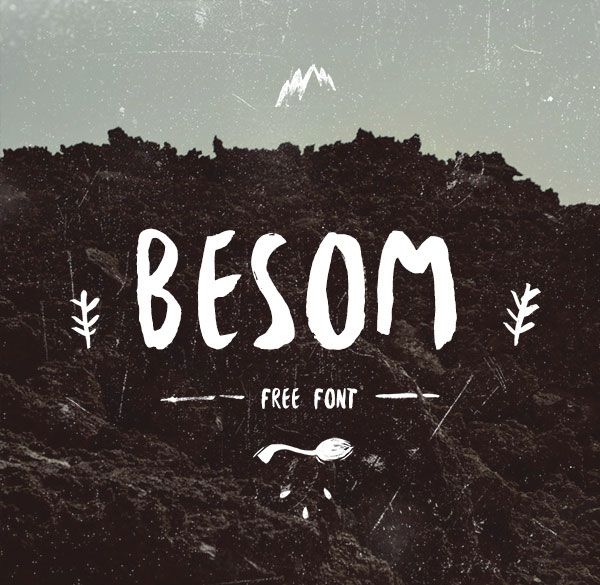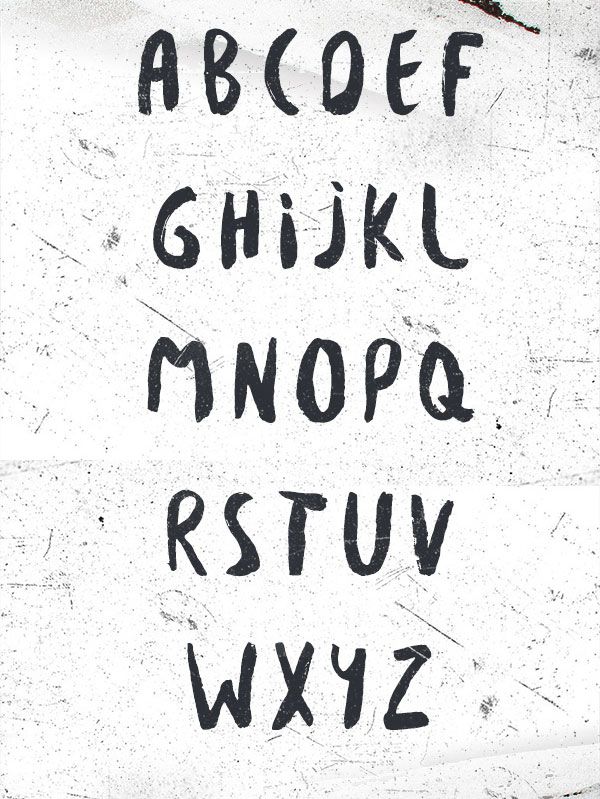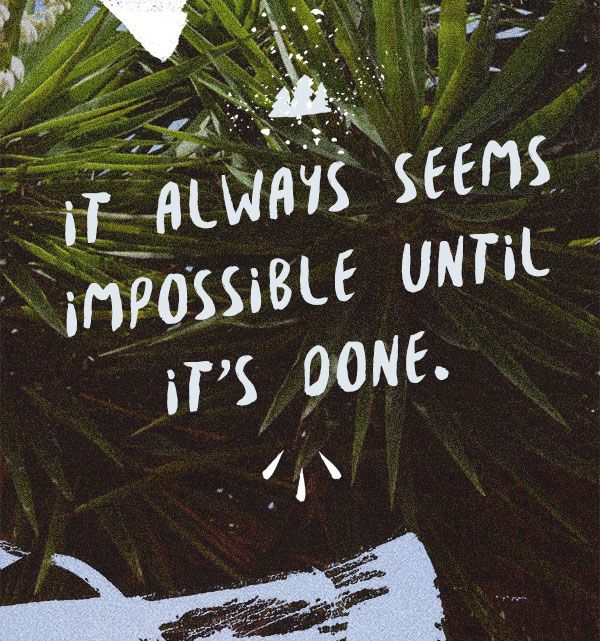
Bonita fuente a mano la que nos trae el diseñador Lituano Krisjanis mezulis bajo el nombre Besom. Una fuente que os vendrá de perlas para esos proyectos donde se requiere una fuente informal. Arrancamos la semana!